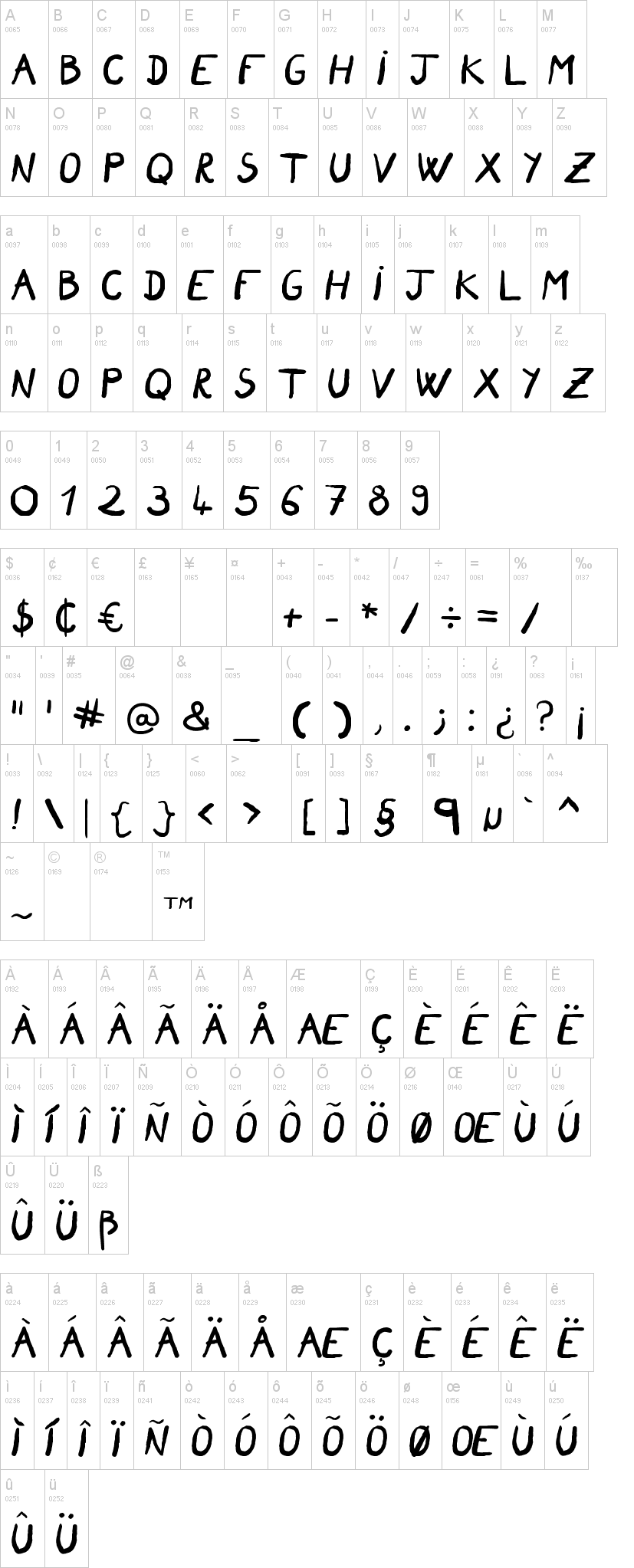
Note of the authorVoici la version complète et gratuite de cette police de caractère, "Foie Canapé".
Elle est dessinée à la base pour le lettrage en Bande Dessinée.